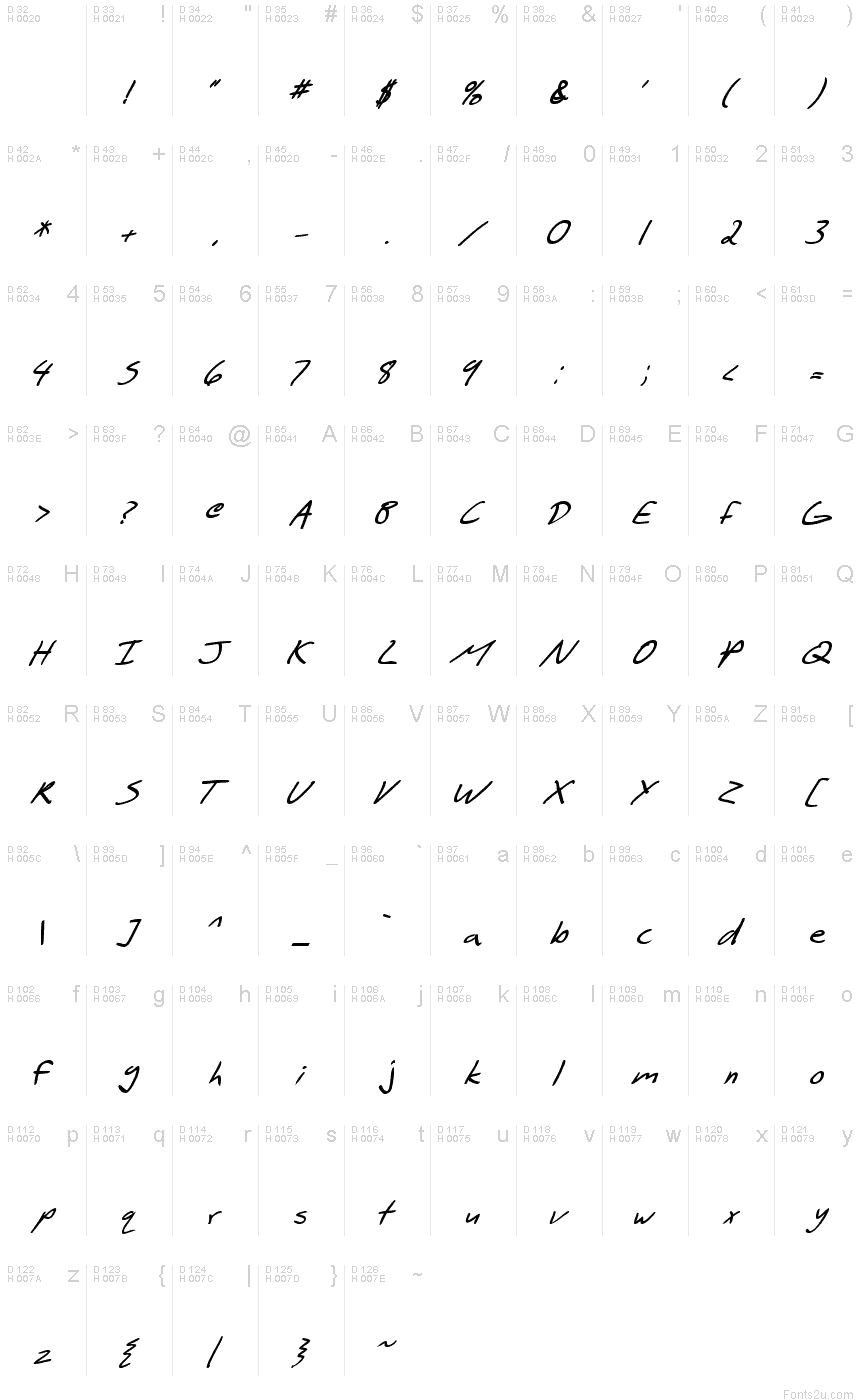
SF Scribbled Sans Bold Italic od ShyFoundry to darmowy, odręczny krój pisma w stylu markera o szybkim, swobodnym rytmie. Litery pochylają się do przodu w szerokich, ciemnych pociągnięciach, łącząc obłe łuki z ostrymi akcentami, dzięki czemu cały projekt sprawia wrażenie szybkiego podpisu lub notatki naniesionej na projekt.
Świetnie sprawdza się w nagłówkach plakatów, na okładkach albumów czy zinów, w brandingu stylizowanym na kawiarniane tablice, nieformalnych opakowaniach i tytułach, gdzie darmowy font ma tętnić życiem, a nie być idealnie wygładzony. Ponieważ pismo jest naturalnie pochylone i rozciągnięte, pasuje również do krótkich cytatów, szkiców logo i dużych napisów, które mają być osobiste, a nie starannie wyrysowane.
SF Scribbled Sans
ShyFoundry
Derek Vogelpohl